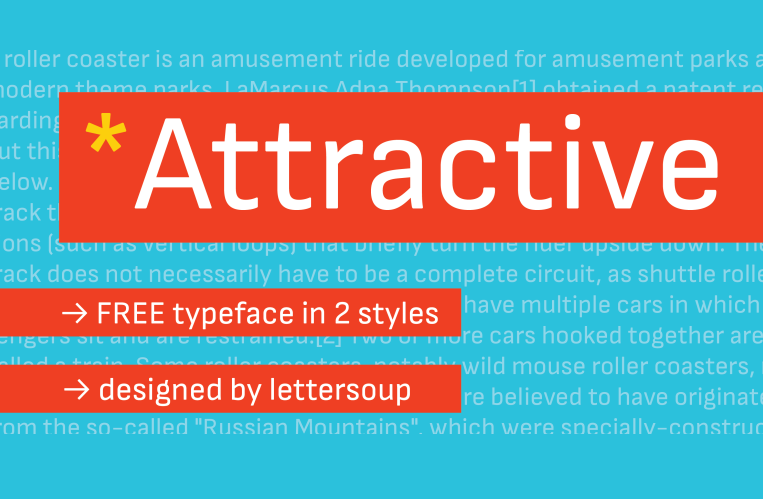
Através do design refinado de Hamilton, apresentamos a Attractive Font Family, uma família de fóntes sans serif que transborda elegância e sofisticação. Inspirada nos estilos técnicos dos anos 1900, essa famosa fonte incorpora detalhes humanos para conferir um toque mais amigável sem comprometer sua simplicidade visual. Oito estilos estão disponíveis: Regular, Italic, Bold, Bold Italic, SemiBold, Semibold Italic, ExtraLight e UltraLight. O extenso atendimento às letras gregas e cirílicas complementa a perfeição do design latino. Com seus contornos otimizados, Attractive mantém um charme orgânico que não é reduzido ou desvirtuado por seu formato de fóntes, fazendo-a uma escolha excepcional para aplicações em pequenas dimensões e grandes formatos. Ideal para editoriais, rótulos, panfletas, sites e demais designers digitais. Além disso, sua versatilidade é perfeita tanto para fontes de texto quanto para elementos gráficos de design web e impressão.